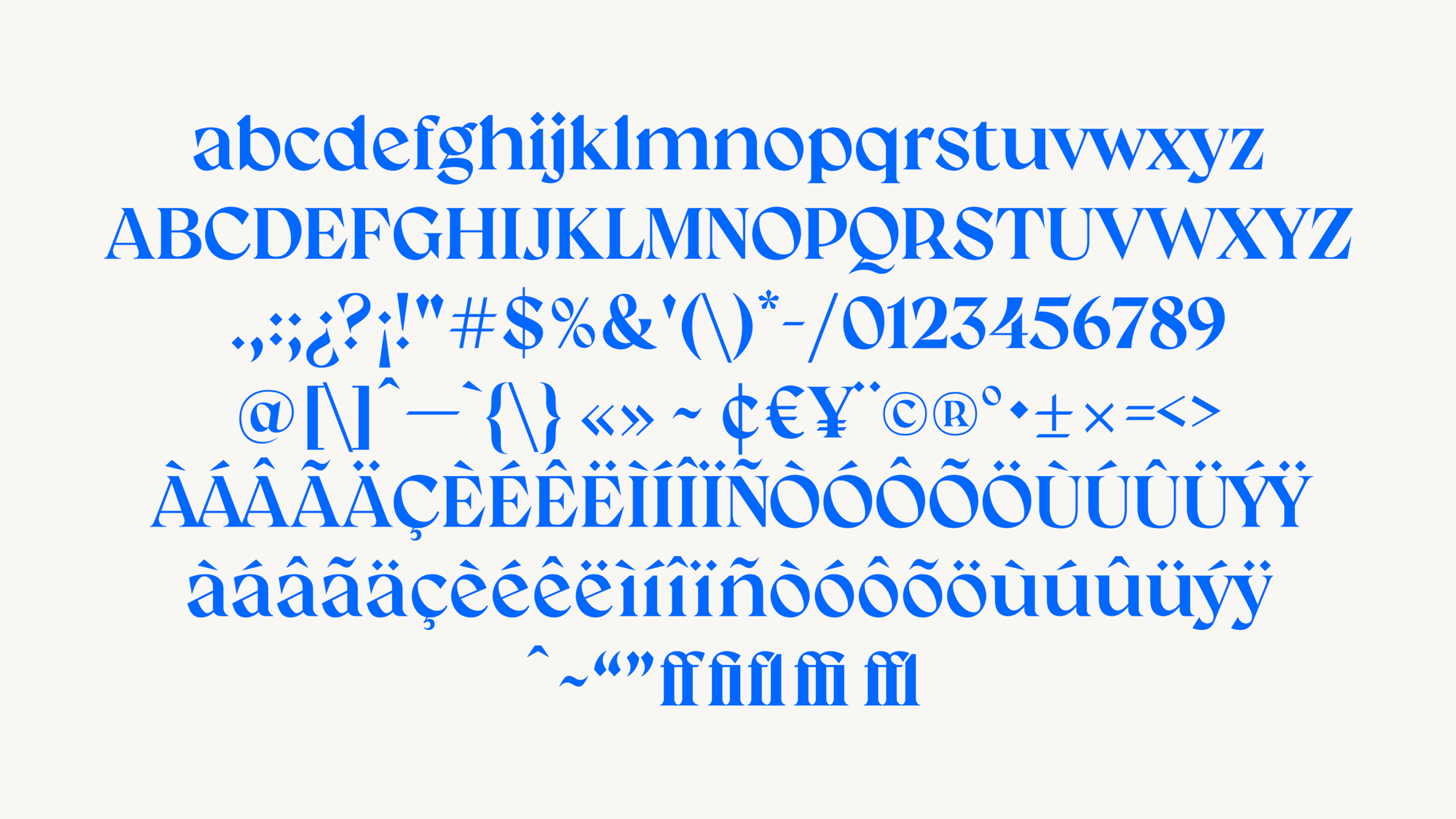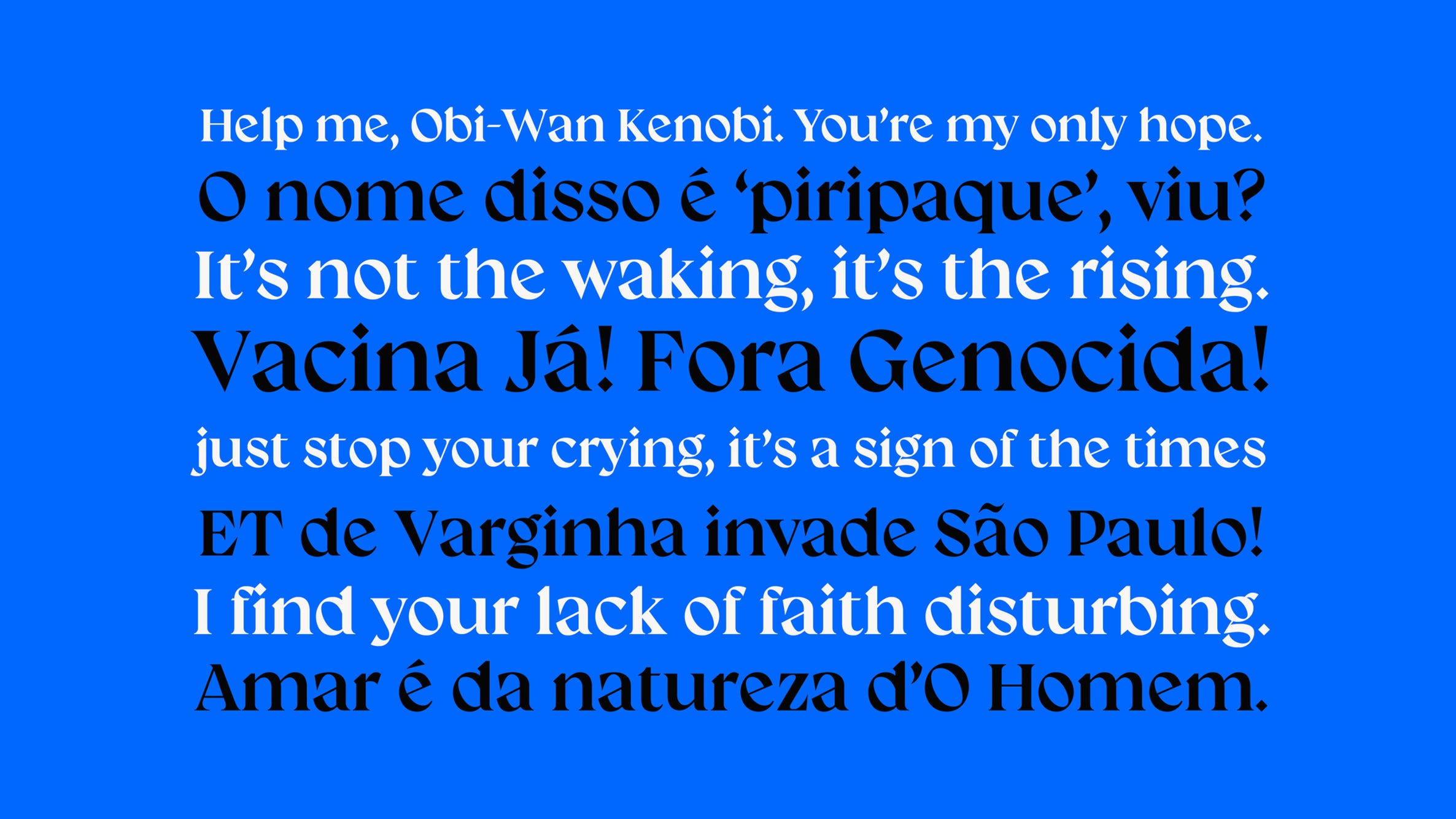
Tipo Aquilo #71 – Escribas, escritoras e Cristina
Um olhar de escrita e gênero sobre a vida e obra de Cristina de Pisano
“O Nome da Rosa” é daqueles filmes que, um dia, espero ter paciência para ler o livro de origem, escrito por Umberto Eco. Além de um belo filme, é daquelas obras que colocam o espectador num tempo em que a igreja era o único caminho para alguém que quisesse estudar e fazer algo mais da vida do que carpir ou guerrear, com toda a chatice dos ritos católicos no meio. Se você viu o filme, já sabe que eu quero falar da cena do escritório e dezenas de escribas caligrafando, fazendo iluminuras e tecendo volumes, fólio por fólio. Se você tiver a sorte de visitar a Abadia de Mont Saint-Michel, no norte da França, pode visitar esse salão em que praticava-se, além da escrita, outras artes voltadas à confecção de livros, como a produção de papel, tintas, penas e encadernamento.
A imagem do escritório do filme, cheio de monges e frades homens, faz a gente pensar que o universo da escrita medieval era excluivamente masculino. Só que sempre houve mãos femininas, mesmo que discretas, empunhando penas e tecendo belas letras. Se você não lê o Contraforma, da Flavia Zim, tem perdido uma sequência incrível de textos sobre mulheres na tipografia contemporânea e as fontes que elas têm produzido. Hoje, trago a história da primeira escritora profissional da Europa — tanto autora quanto calígrafa —, aprofundando em curiosidades da atividade de caligrafia na baixa Idade Média e comentando sobre as circunstâncias que permitem tecer algumas palavras de reverência à poetisa Cristina de Pisano.
A vida de Cristina, ao menos para a história do ocidente, é um de vários pequenos eventos que ilustram a passagem do mundo da Idade Média para a Moderna. Ela nasceu em setembro de 1363, na antiga República de Veneza. Seu pai, Tomás de Pisano, era astrônomo (ou astrólogo, nessa época não tinha diferença) e conselheiro da república, até aceitar um convite do Rei Carlos V da França para ser seu astrônomo real, alquimista e médico em 1368. Com isso, Cristina e sua mãe mudaram-se também para Paris. Não se sabe a identidade de sua mãe e pouco é sabido sobre sua infância, além de que ela cresceu no seio da corte francesa e tinha acesso a várias de suas bibliotecas. Aos 17 anos, Cristina casou-se com Etienne de Castel, secretário da chancelaria real, com quem teve três filhos. Etienne não opôs-se aos estudos de Cristina, permitindo suas primeiras aventuras na escrita.
Embora a vida de Cristina parecesse fortuita, em 1386, seu pai morreu deixando dívidas para a família. Em 1389, Etienne foi vitimado pela peste, e ela teve diversos problemas jurídicos para ter sua herança reconhecida. Com o pai e o esposo mortos, viu-se na dura situação de sustentar sozinha a mãe e suas três crianças. Um novo casamento com algum homem de posses era o caminho mais esperado para jovens viúvas em sua época; no entanto, apostou seu destino na vida literária, dedicando-se a escrever e produzir, inicialmente, volumes de poesias e histórias de amor. Alguns destes livros, que tinham seu envolvimento direto na própria escrita e na direção artística de ilustrações e miniaturas, eram dedicados a nobres e mecenas que circundavam a corte francesa, que garantiram sua segurança financeira.
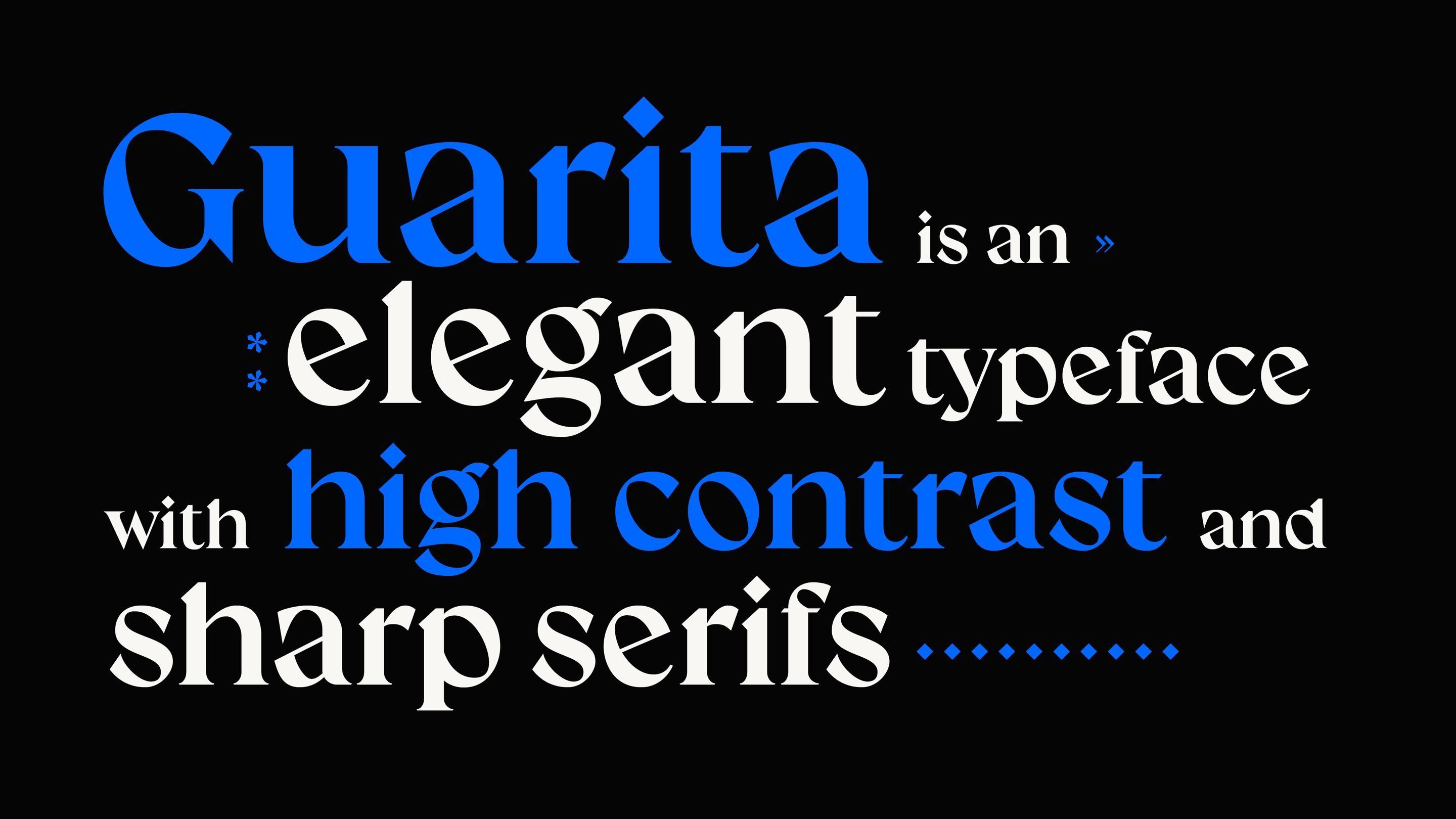
“Mas Cadu, ela escreveu mesmo? Escrever não era coisa só de homens? Caligrafia não era coisa só da igreja? E o que quer dizer ‘miniatura’? CADU MIM AJUDA”
Calma, vamos por partes. Primeiro, sobre a escrita fora da igreja, um processo desencadeado pela formação das universidades que criou uma grande demanda por livros que a igreja sozinha não dava conta. Juízes, escrivões e outras figuras do direito medieval também passaram a redigir documentos oficiais por conta própria, tirando dos mosteiros o monopólio da escrita. A escrita blackletter, mais comprimida e modular do que os modelos caligráficos anteriores, mostrava uma secularização da produção literária, cada vez menos voltada para a própria igreja e mais para o conhecimento secular. A economia de papel que o uso da blackletter proporcionava fez com que a escrita fosse adotada como padrão em quase toda a Europa… exceto na Itália, que sempre torceu o nariz pra tudo que não era greco-romano.
Desde o séc. III, várias calígrafas notáveis destacavam-se nos impérios árabe, persa e chinês. Na Europa, os relatos do bispo Eusébio de Cesareia falam de freiras copistas desde as primeiras décadas da Igreja Católica, que abriram caminho para outras calígrafas famosas como Diemoth, Clara Hätzlerin e Jacomina Hondius. A vida de Cristina lembra a de outra mulher importante para a história francesa, a Condessa Mahaut de Artois, que também não casou-se após perder o primeiro marido e foi uma importante patrona para artistas locais. Também é longeva a autoria feminina de poesias e canções durante a Baixa Idade Média, em que, ao lado de Cristina, aparecem outras mulheres como Hildegarda de Bingen, Catarina de Sena e Margery Kempe.
Cristina representa uma convergência em vários desses caminhos que outras mulheres ajudaram a criar. Suas obras fizeram sucesso e permitiram que ela vivesse de sua própria produção artística. Além de autora, ela também era copista, tendo literalmente escrito vários livros que fez. Cristina também fazia a direção de arte das ilustrações de seus livros, orientando os artistas que criavam as miniaturas ao redor do texto. Ah sim, sobre miniaturas… você deve conhecer as iluminuras, ilustrações medievais ao redor dos textos, certo? Enquanto as miniaturas utilizavam pigmentos comuns, as iluminuras ostentavam tintas douradas que “iluminavam” as páginas. Ainda que os dois termos possam ser usados para a mesma coisa, tecnicamente, o uso do pigmento dourado diferencia ambos.
Durante a produção dos livros, os trechos tinham pequenas inscrições numeradas que identificavam cada copista; por exemplo, se um volume fosse manuscrito por oito escribas, cada uma era identificada de “Mão I” a “Mão VIII”. Algo que permite-nos afirmar que Cristina era mão de vários de seus livros é a presença de sua assinatura como “xpine de pizan”. Se vocês aventurarem-se pela paleografia, verão o uso constante de abreviaturas em documentos que exigem (muita) interpretação e contextualização. O “xp”, neste e em outros casos, é uma referência a Cristo: o “x” vem da letra grega “χ” (chi) e o “p” vem da letra “ρ” (ro). Em manuscritos de língua portuguesa, por exemplo, existiam abreviaturas como “bpõ” (bispo), “livº” (livro), “pmº” (primeiro) e outros que agilizavam a escrita. Assim, coisas relativas a Cristo ou que tinham nome derivado dele usavam a abreviatura “xp”, como a xpina… digo, Cristina.
No entanto, ao invés de preservar sua obra como bela, recatada e do lar, com o passar do tempo ela questiona o tratamento dado às mulheres na literatura e na sociedade medieval nas obras que escreveu em resposta ao “Romance da Rosa”, em que Jean de Meun retrata o feminino, segundo Cristina, como um mero objeto de sedução. Imbuída de mostrar a misoginia presente na representação feminina de Jean e outros autores medievais, ela escreve seus títulos mais célebres que dão início à Querela das Mulheres. “O Livro da Cidade das Damas” e “O Livro das Três Virtudes”, por exemplo, trazem uma utopia de uma cidade povoada apenas por mulheres, e como estas devem agir para que tornem-se tão virtuosas quanto as grandes mulheres da história, habitantes da cidade idílica criada por Cristina. A “Epístola ao Deus do Amor”, por sua vez, é uma crítica direta à misoginia presente na obra de Jean.
Ao longo de sua vida, Cristina escreveu vários textos ficcionais e não-ficcionais, em que narrou a vida de monarcas como o próprio Carlos V, e manuscritos como “O Livro da Transformação da Fortuna”, onde a narradora conta as mudanças que Fortuna impõe-lhe desde a tragédia da perda do marido até o momento em que ela torna-se o homem escritor dos versos do livro. Embora a transformação da obra tenha um cunho autobiográfico, referindo-se a como as atividades de escrita teórica e política feitas por Cristina eram vistas como “masculinas”, a obra não deixa de ser um exemplo de questionamento dos papeis de gênero na sociedade e uma pré-literatura trans.